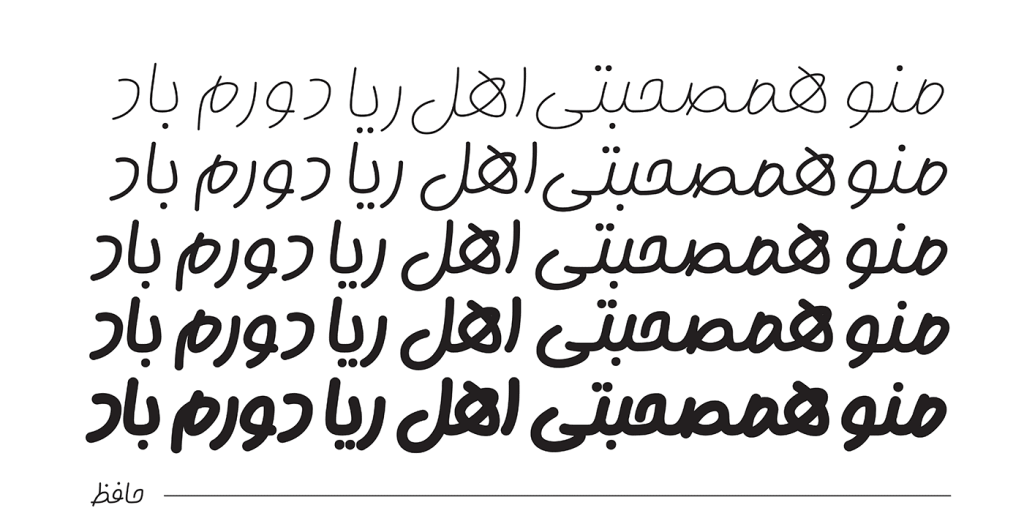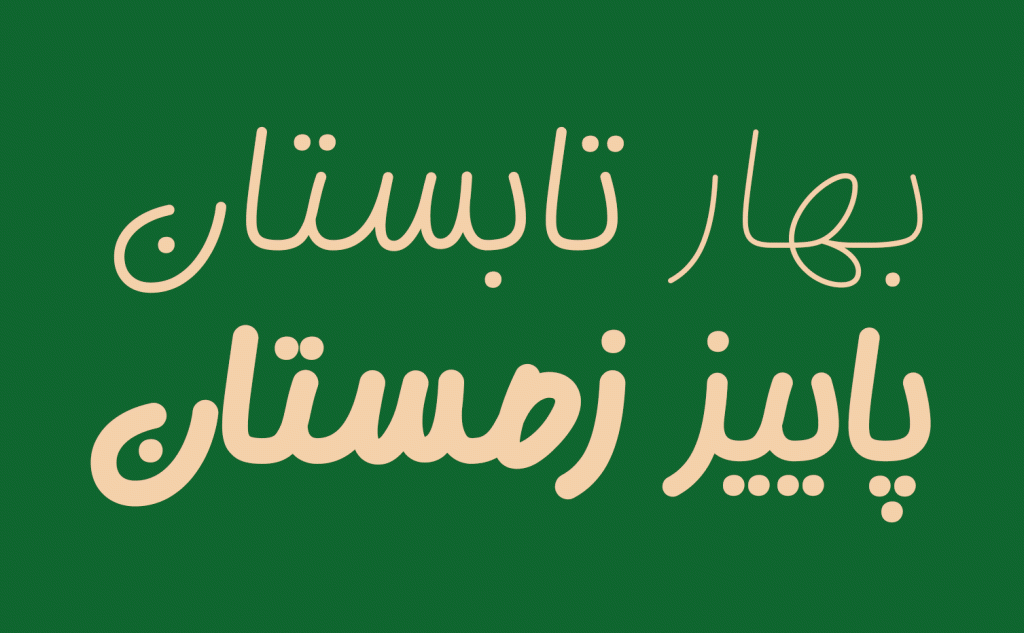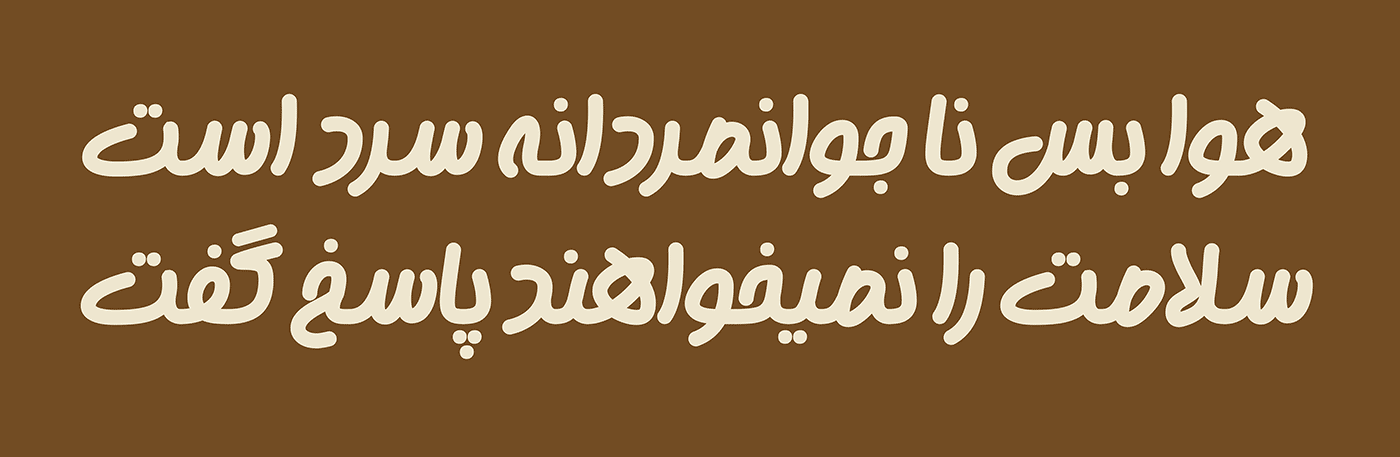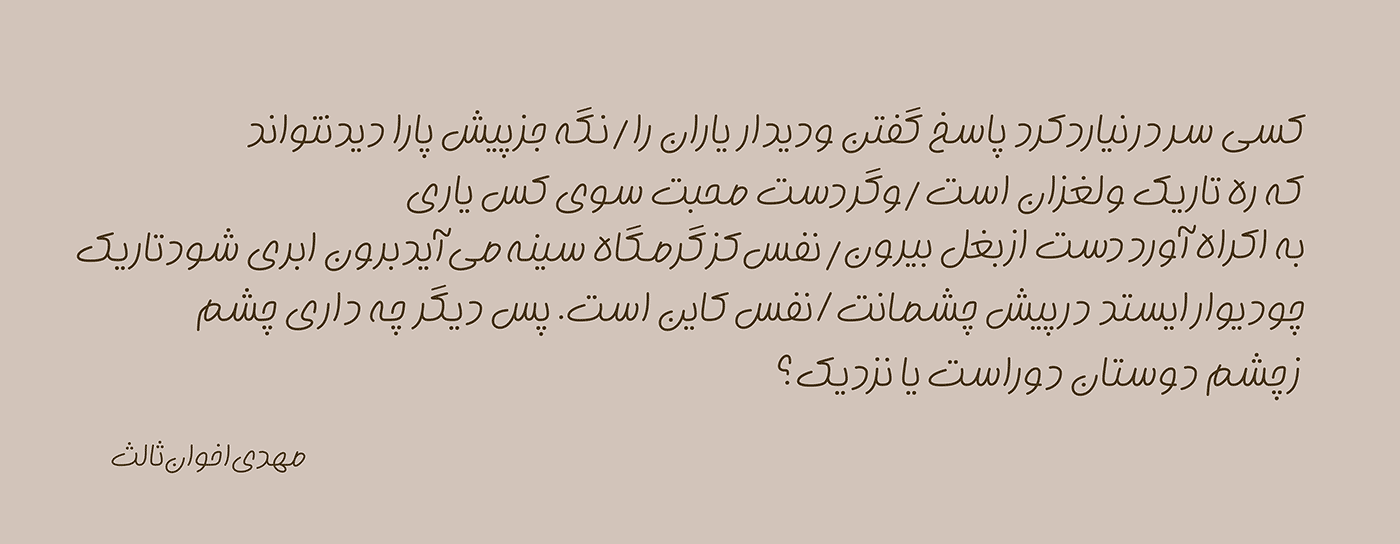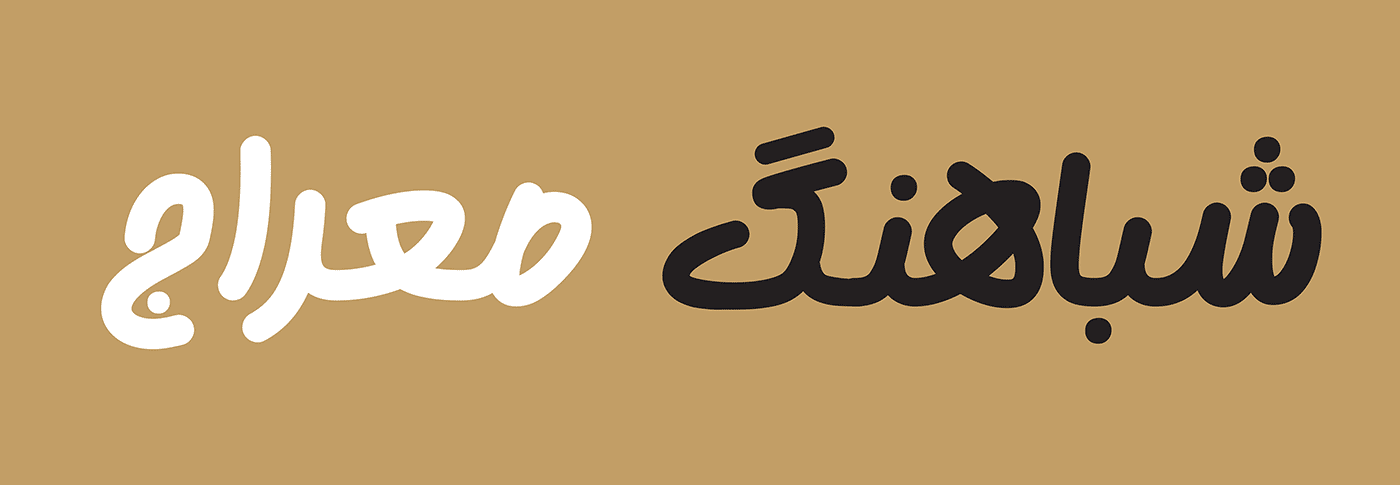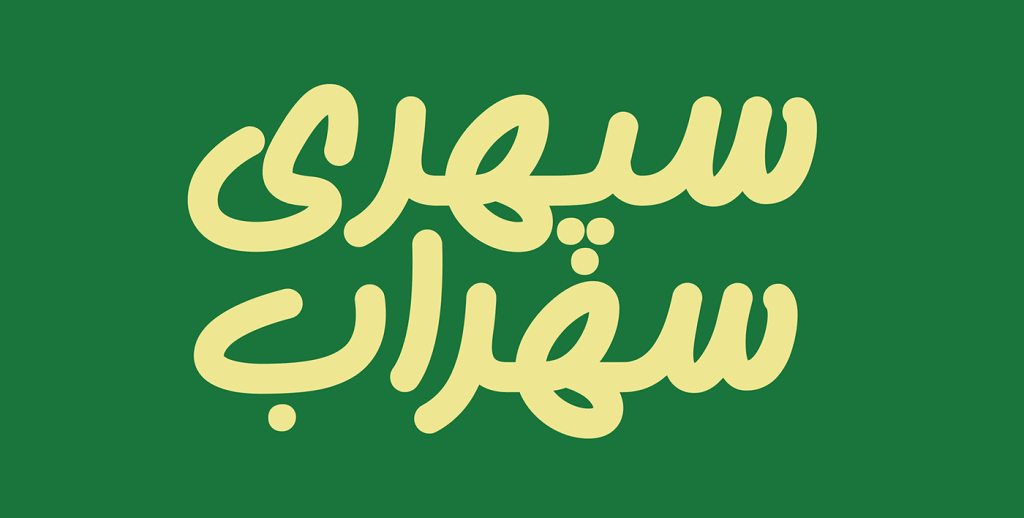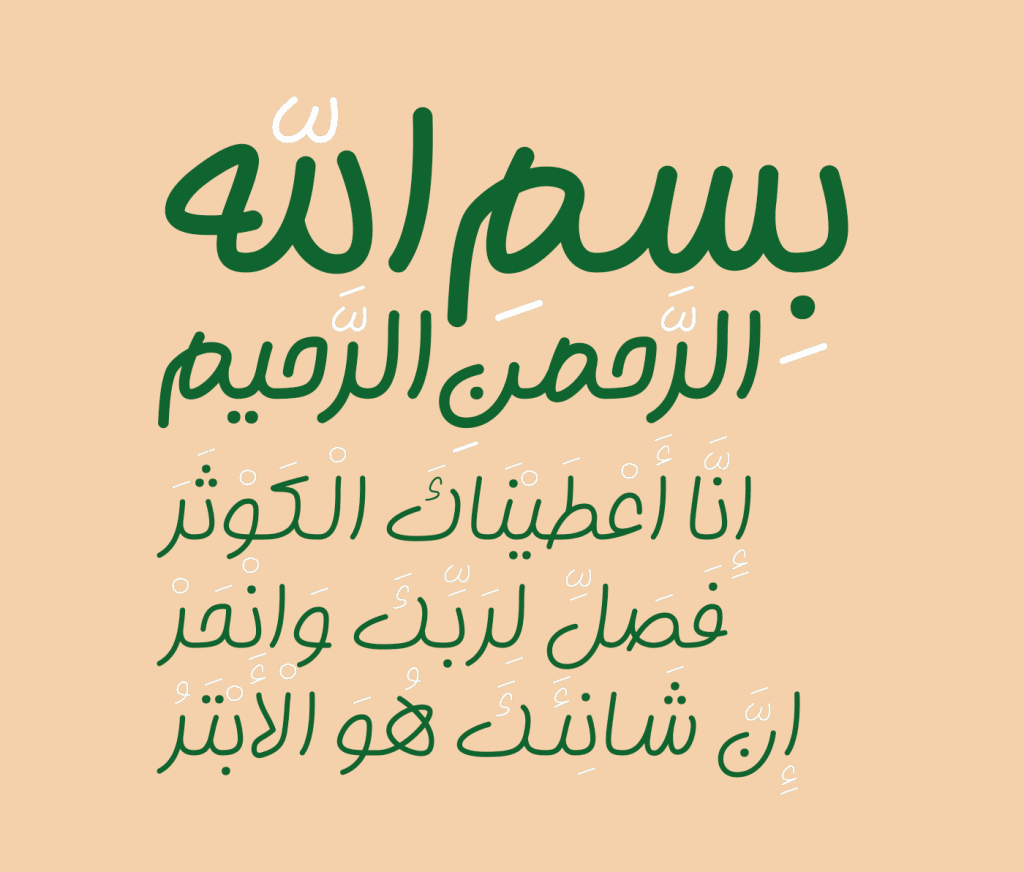
فونت گوهر از دسته تایپ فیس های خانواده دست نویس، توسط طراح نام آشنا آقای مصطفی اوجی طرحی شده است . با ما همراه باشید تا این قلم زیبا و جمع و جور را به شما معرفی کنیم.
فونت گوهر قلمی زیبا از خانواده دست نویس
فونت گوهر همانطور که پیش تر گفته شد توسط آقای مصطفی اوجی که از اساتید با سابقه تایپوگرافی فارسی است طراحی گردیده. با کمی دقت در فرم طراحی حروف و گلیف های این تایپ فیس می توان دریافت که بدون کنتراست در سطح و از دسته قلم های منو لاین است.ویژگی اساسی گوهر سادگی و بی آلایشی آن است.
به سبب نزدیکی به دست خط انسان و بهره بردن از منحنی های منعطف و دوری از زوایای تند و تیز ارتباطی گرم و صمیمی با مخاطبین خود برقرار می نماید . همچنین عدم وجود زوایه های تند و تیز در طراحی این قلم بر روانی و به نوعی ملایمت در ظاهر جهت ارتباط با مخاطب را همانگونه که پیش تر نیز گفته شده بود می توان مشاهده کرد.
با کمی دقت در ساختار این تایپ فیس در می بابیم که گوهر دارای کمی فشردگی در فرم و به اصطلاح جمع و جورمی باشد که سبب ایجاد برای سطرهای منسجم و فشرده‌ای شده است. حرکت های حروف به رغم رهایی حرکات قلم، فرم‌های کنترل شده‌ای‌ دارند.
این تایپ فیس در 5 وزن طراحی گردیده که پاسخ دهنده به نیاز های شما را در انواع اوزانمی باشد. در زیر تصاویری نمونه از این قلم برای شما عزیزان آماده گردیده است. همچنین می توانید این قلم را با 5 درصد تخفیف دانلود و خرید کنید. کافی است از طریق لینک زیر به سایت مرجع ورود و کد fontziba را در قسمت کد تخفیف وارد نمائید.